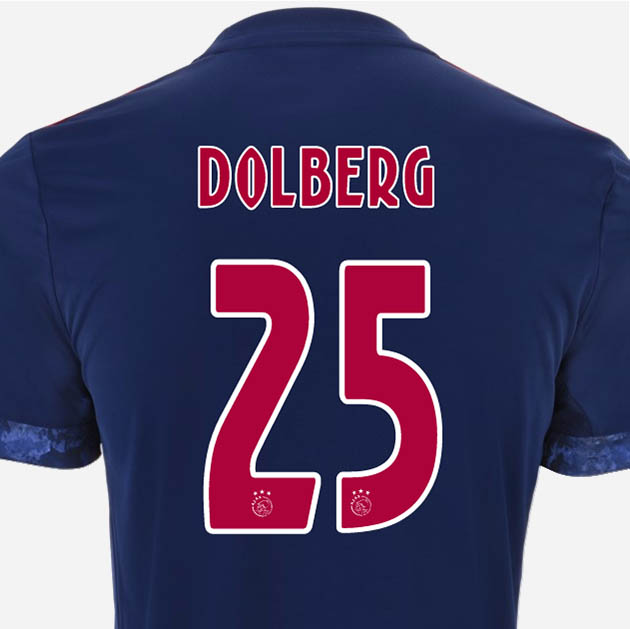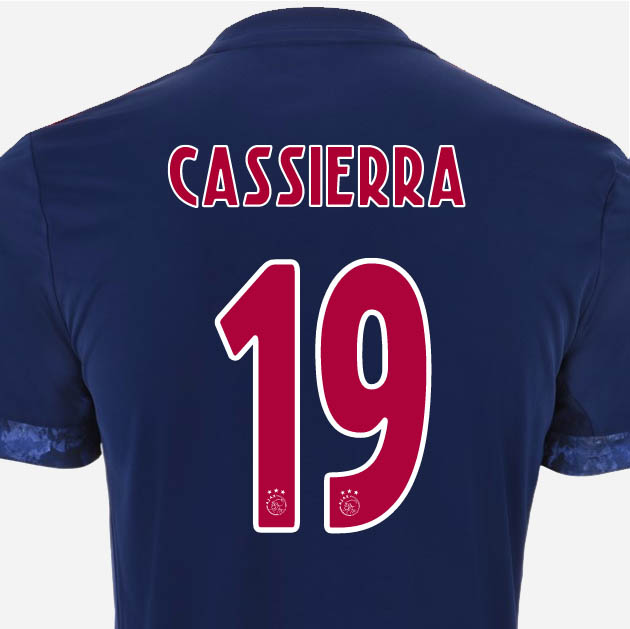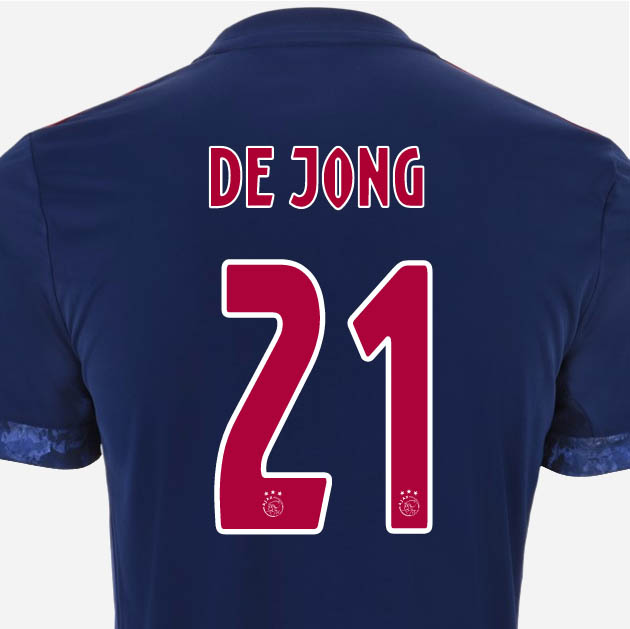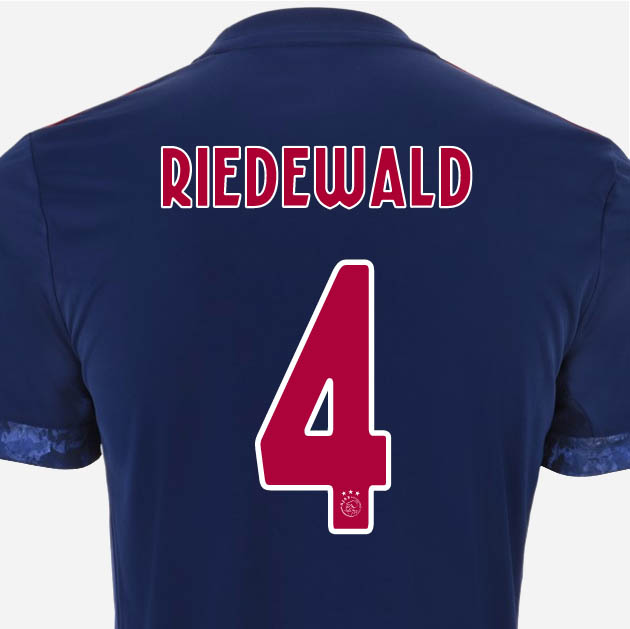
Völlig neue Ajax 17-18 Trikot-Schriftart enthüllt
Der 2017 Europa-League-Finalist Ajax hat nicht nur zwei brandneue Trikots für die Saison 2017-2018 enthüllt - der niederländische Klub hat auch eine völlig neue Schriftart für die Trikots der nächsten Saison präsentiert.
Ajax Amsterdam 2017-2018 Trikot-Schriftart
Hier ist die neue Ajax-Schriftart auf dem 2017-18 Auswärtstrikot.
Die neue Ajax 2017-18 Schriftart weist ein Design auf, das weniger außergewöhnlich als die Schriftart auf den Trikots der letzten Saison ist. Die Nummern der neuen Ajax 17-18 Schriftart setzen auf runde Ecken, während die Buchstaben ein ungewöhnlicheres Design aufweisen.
Letztjährige Schriftart
Am unteren Ende der neuen Ajax 2017-18 Trikot-Nummern ist Ajax Wappen. Die Adidas Ajax 2017-2018 Schriftart auf dem Heimtrikot wird weiß sein, während es noch kein Bild der Schriftart gibt.